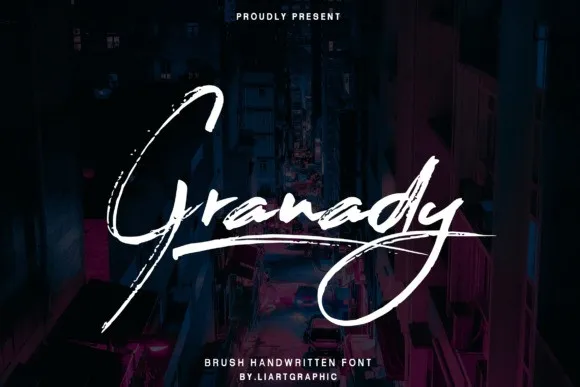
A Granady Font é uma tipografia círculo de tinta desenvolvida pelo designer sifak1726. Com seu traço natural de espartilho, caracteres inclinados e um ar divertido com algumas ligas e versões alternativas das minúsculas, ela apresenta um visual único que se destaca para uma ampla gama de ideias criativas. Seja para os selinhos e títulos, ou até mesmo para papelaria personalizada, a Granady Font oferece uma maneira única de tornar seu trabalho ainda mais singular.